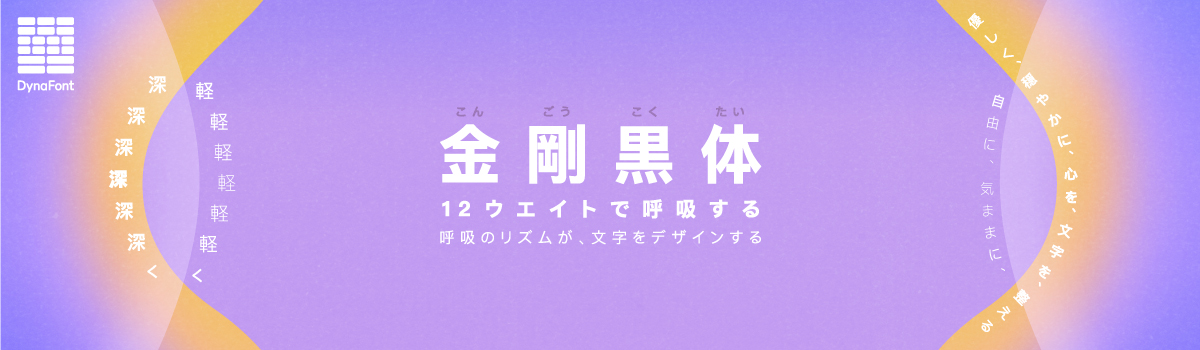
ダイナコムウェアは、ダイナフォント年間ライセンス「DynaSmart V」「DynaSmart 教育機関向けプラン」「DynaSmart 学生版」ユーザーに向けて、DynaFont(ダイナフォント)2022年日本語新書体として、ダイナコムウェアのフラッグシップフォントである「金剛黒体(こんごうこくたい)」の新ウエイト「金剛黒体Bold 6ウエイト」を含む、ダイナフォント26書体を2022年4月21日(木)より提供を開始したことを発表した。
その他にも、楽しさを表現したPOP系書体「POP1体W3/W5/W7/W9/W12」、「POP2体W9/W12」のOpenTypeフォントStdN版や、エレガントな雰囲気のロマン風書体「欧風花体W5」のTrueTypeフォント版を追加収録した。
また、「金剛黒体Bold 6ウエイト」のリリースを記念した「金剛黒体」新動画も2022年4月21日(木)から公開した。
「金剛黒体」新6ウエイト
「金剛黒体」は、グローバル化するデジタル環境向けにデザインされたゴシック体フォント。100ヶ国以上の国や地域のデジタルデバイスに対応可能な18言語で展開し、液晶表示での高い視認性、息吹を感じる柔らかな設計、各言語本来の美しさを追求したデザインにより、異なるインターフェースや言語においても人の温もりを以て情報を伝達する。
日本語書体としても、これまで6ウエイトおよび、C90、C85、C80、C75の4種類のコンデンス書体をリリースしており、そのコンセプトやデザイン性は国内外で高い評価を受け、グッドデザイン賞など国際的なアワードを多数受賞している。
「金剛黒体」は、Ultralight、Thin、Light、Regular、Medium、Semiboldの6ウエイトで展開してきましたが、さらに太いウエイトにも対応して欲しいというユーザーから寄せられる声を受け、Bold書体の開発を進めてきた。
そして2022年4月21日(木)より、Bold、Extrabold、Ultrabold、Black、Extrablack、Ultrablackの6ウエイトを、それぞれの太さに合わせた読み心地を追求した設計にてリリースした。
▼「金剛黒体」国際的なアワード多数受賞
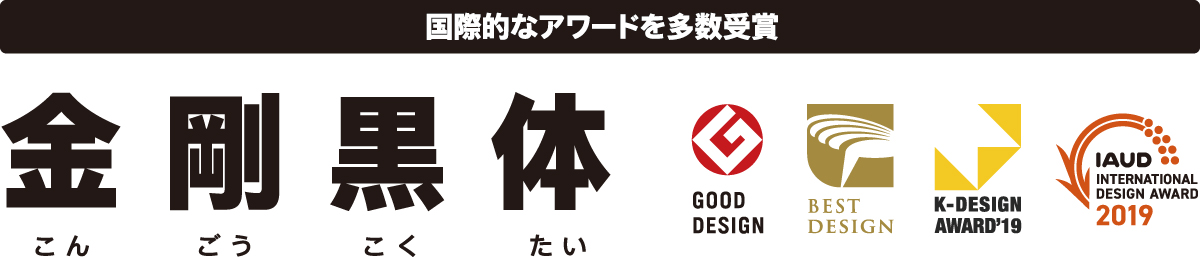
▼「金剛黒体」日本語書体×12種類のウエイト
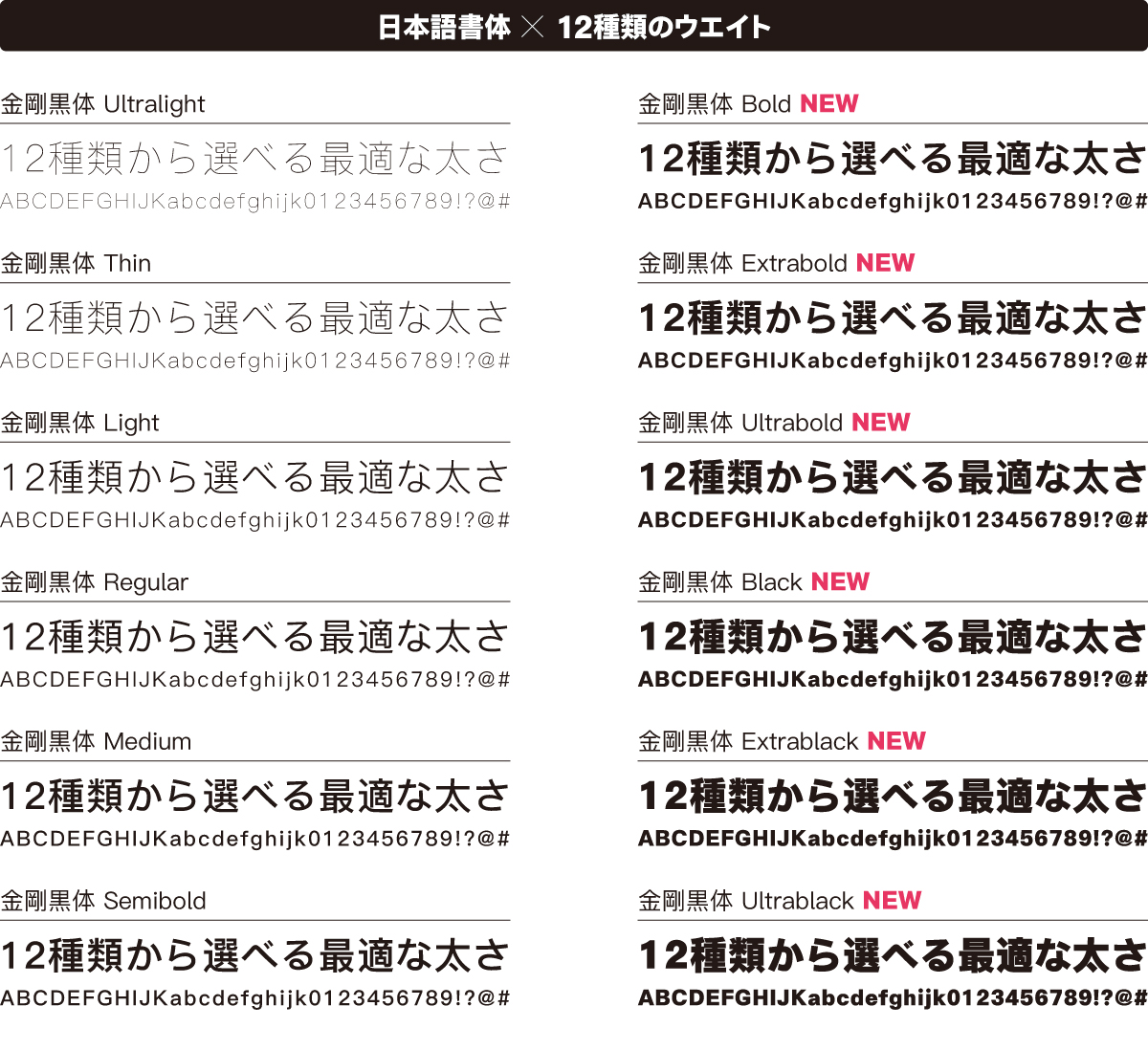
▼「金剛黒体」4種類の横幅×6種類のウエイト
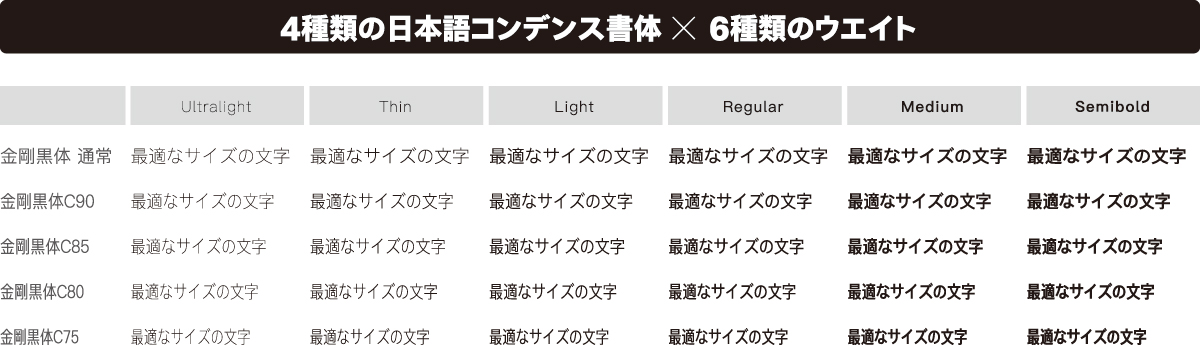
▼「金剛黒体」18種類の多言語×6種類のウエイト
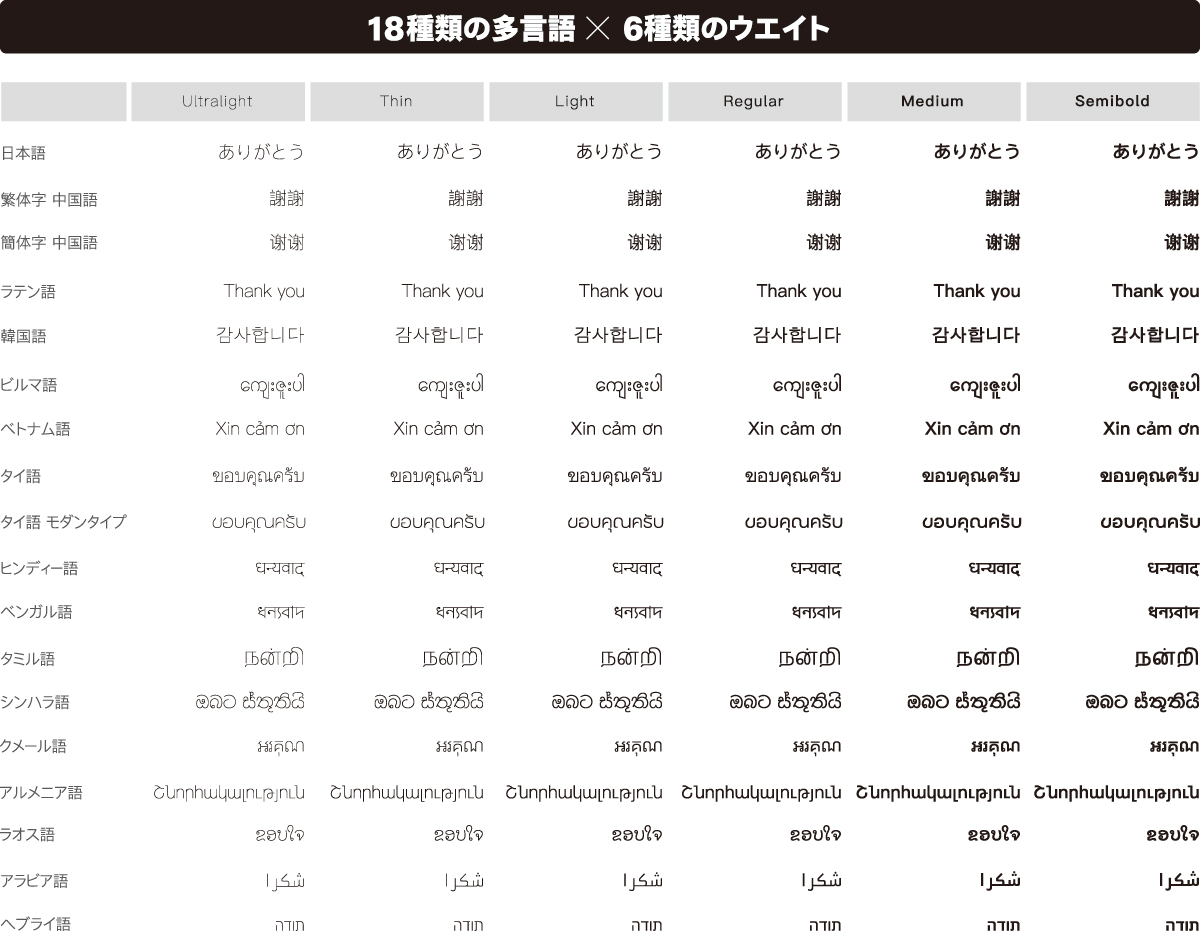
▼「金剛黒体」活用例
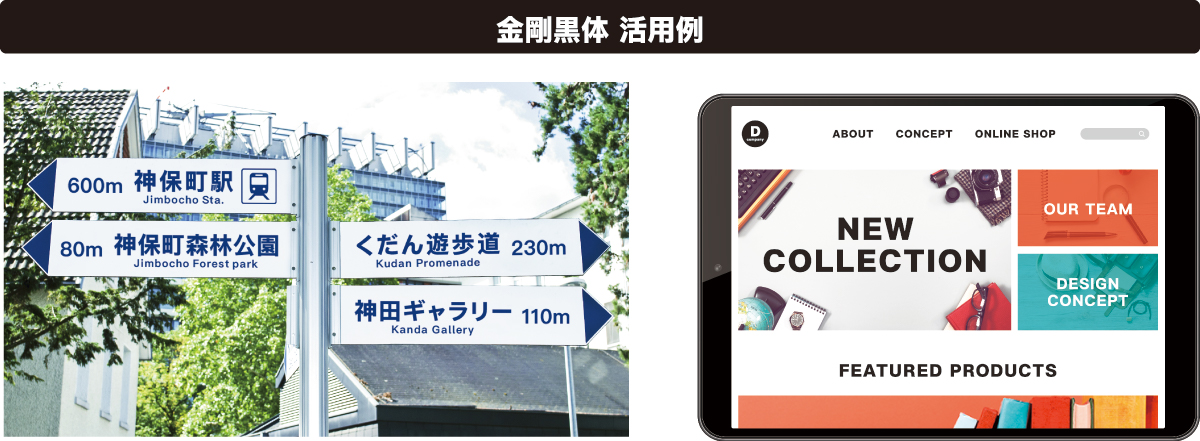
TrueTypeフォント版「欧風花体」
「欧風花体」は、リズミカルな筆遣いの文字にループが彩られた、見る者の心を揺さぶる洗練された書体。文字が華やかな衣装を身に纏って、軽やかに舞っているような姿にも見える。華やかで美しい欧文の手書き文字を参考に、漢字や平仮名のデザインにもカリグラフィー特有の滑らかで抑揚のあるループを取り入れました。全体的に丸みのあるスタイルでありながらも、軽やかさや上品さも感じることができる。